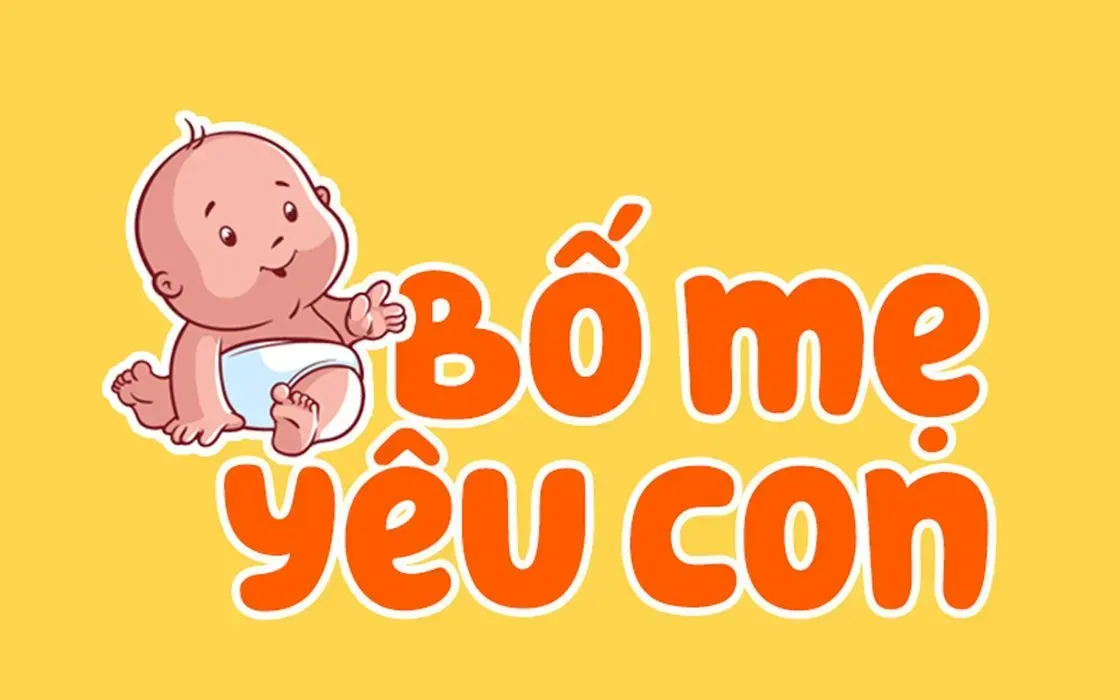
Font chữ SVN Hello Headline – Hoạt hình, Vui nhộn & Việt hóa đầy đủ
SVN Hello Headline là một font chữ sans-serif (không chân) mang phong cách hoạt hình tươi sáng, ngộ nghĩnh và đầy sức sống. Với các nét chữ dày dặn, bo tròn và hơi ngả nghiêng, font tạo cảm giác như bước ra từ thế giới truyện tranh hoặc chương trình thiếu nhi – nơi màu sắc và sự vui nhộn luôn hiện diện.
Từng ký tự trong Hello Headline có hình dáng béo tròn, dễ thương, các đường nét được vẽ gọn gàng nhưng vẫn giữ được chất "handmade" tự nhiên, giúp font trở nên thân thiện và gần gũi với trẻ em. Đây là font lý tưởng cho các thiết kế như:
– Tiêu đề sách hoặc truyện tranh thiếu nhi
– Poster hoạt hình, banner quảng cáo sản phẩm trẻ em
– Bao bì đồ chơi, quần áo trẻ em hoặc bảng lớp mầm non
Font gốc Hello Headline được phát triển bởi nhà thiết kế Cosimo Lorenzo Pancini, thuộc studio Zetafonts – nổi tiếng với các font mang tính cách cá nhân cao, sáng tạo và bắt mắt. Phong cách của font hướng tới truyền thông thị giác vui vẻ, tích cực, rất phù hợp trong lĩnh vực giáo dục và giải trí.
Phiên bản Việt hóa bởi nhóm SVN Fonts đã được xử lý cẩn thận, bổ sung đầy đủ dấu tiếng Việt, đảm bảo font giữ được sự liền mạch, dễ đọc và vui tươi khi sử dụng trong các thiết kế tiếng Việt. Font hoạt động mượt mà trên các phần mềm như Photoshop, Illustrator, Canva và cả môi trường giáo dục số.
Nếu bạn đang cần một font hoạt hình, tròn trịa, vui nhộn và dễ sử dụng, thì SVN Hello Headline là lựa chọn tuyệt vời để mang đến năng lượng tích cực và nét hồn nhiên cho mọi thiết kế liên quan đến trẻ em, giáo dục và giải trí sáng tạo.